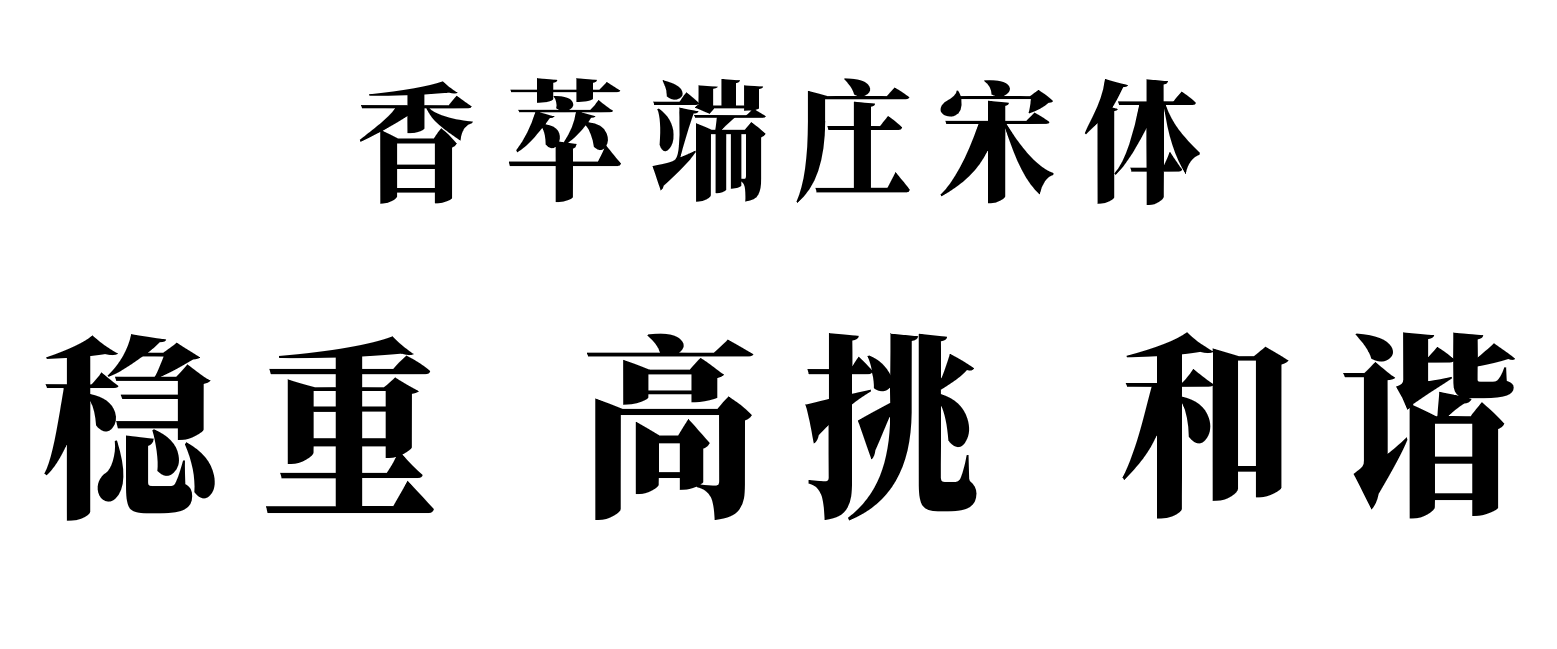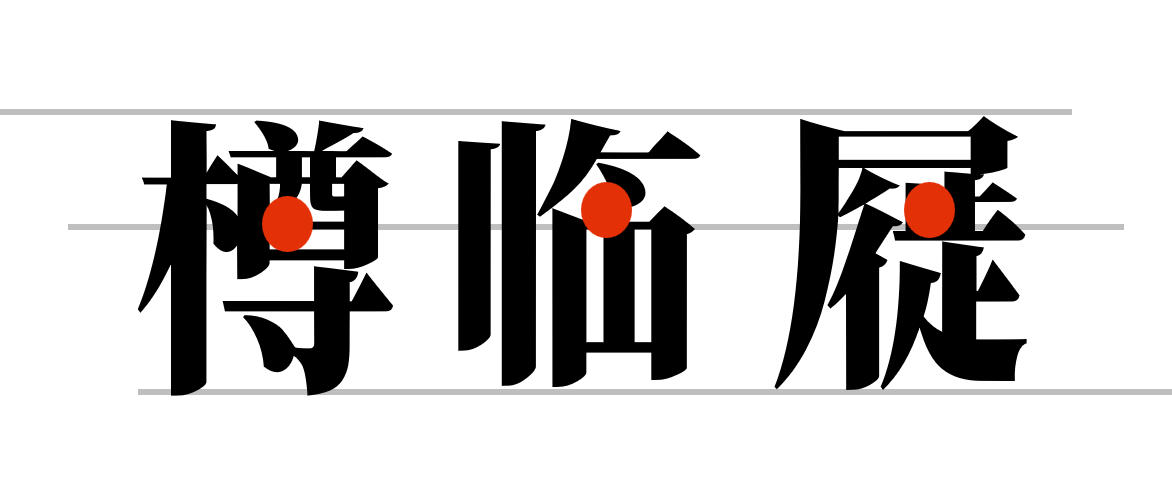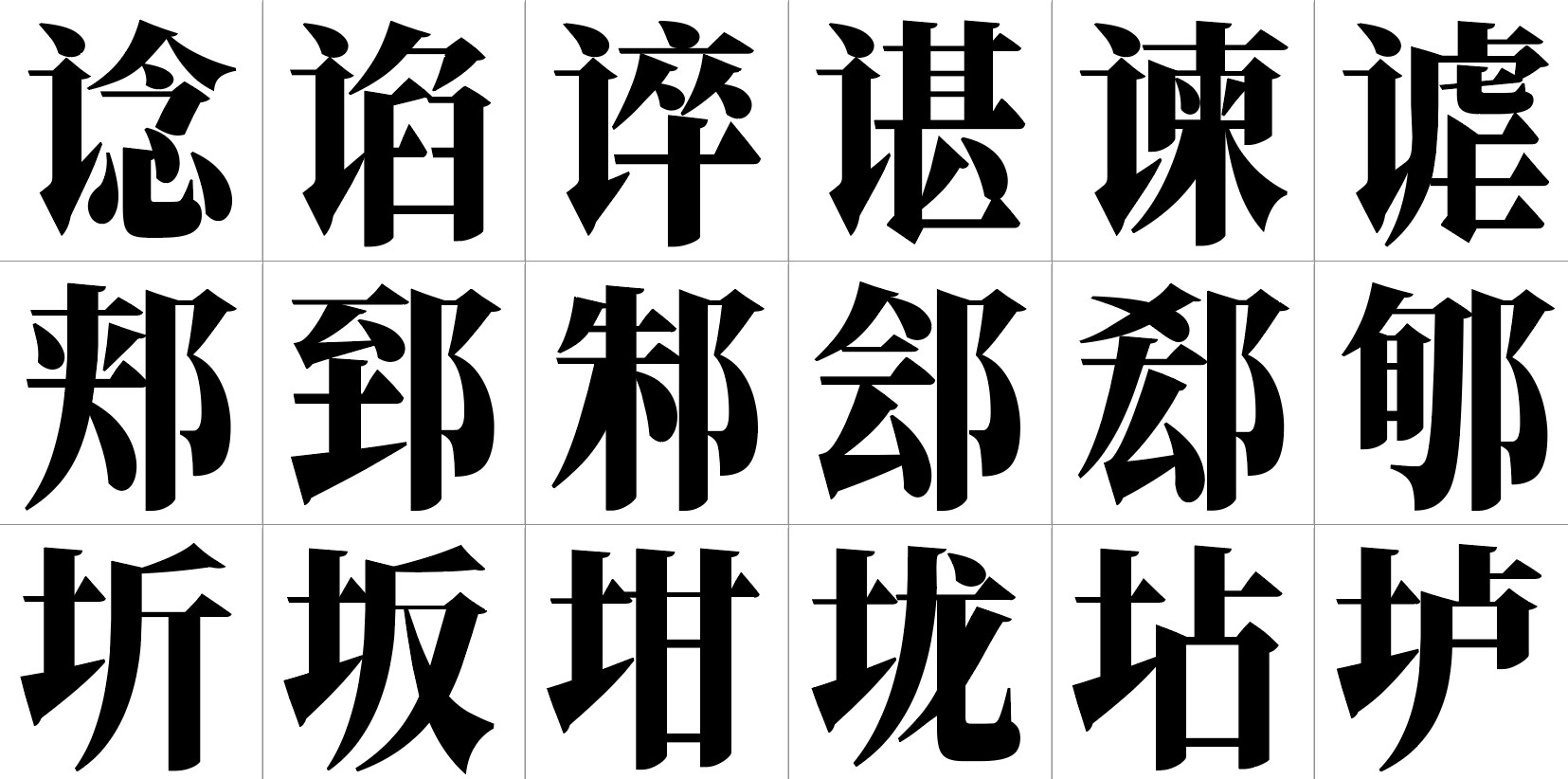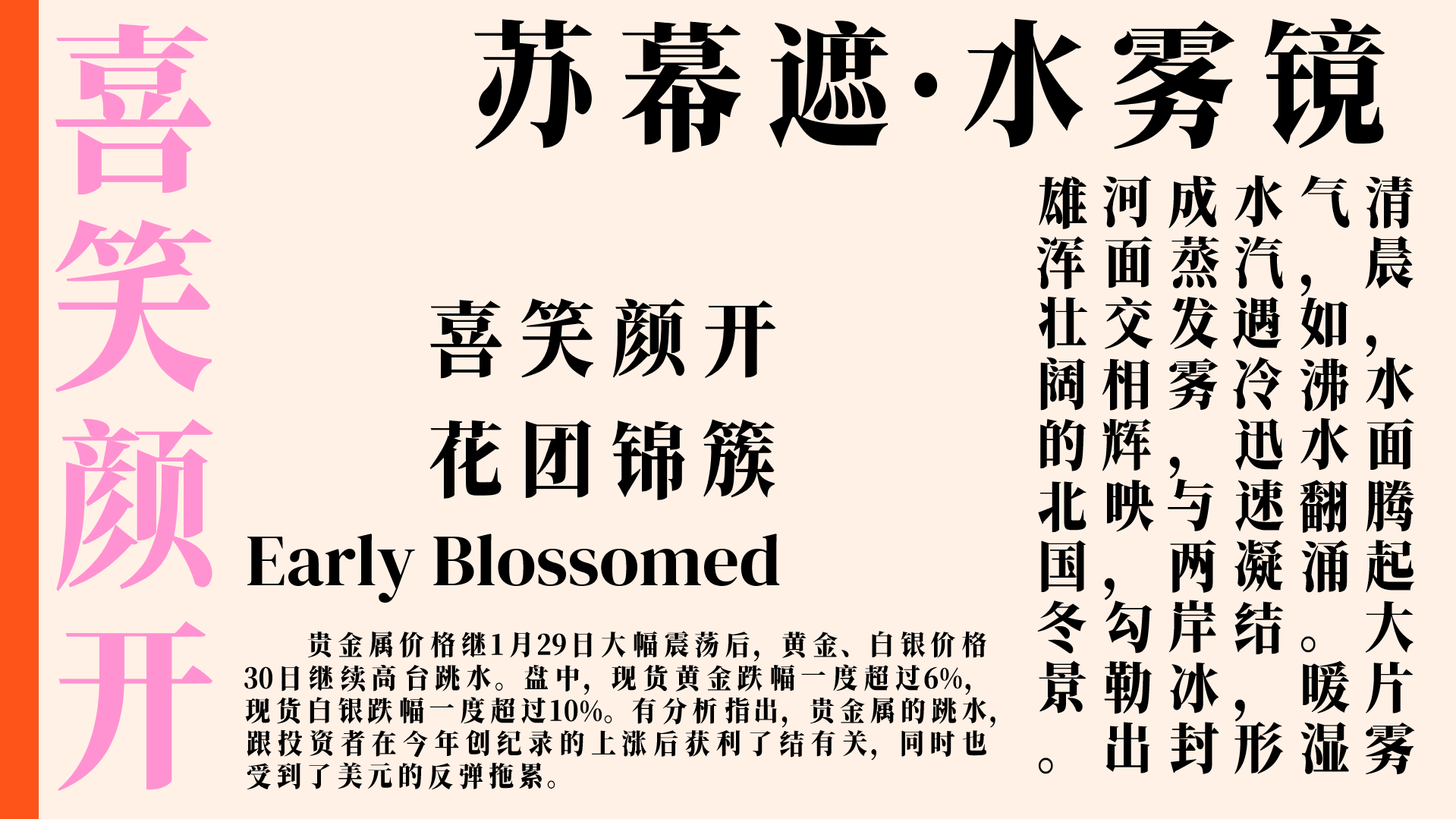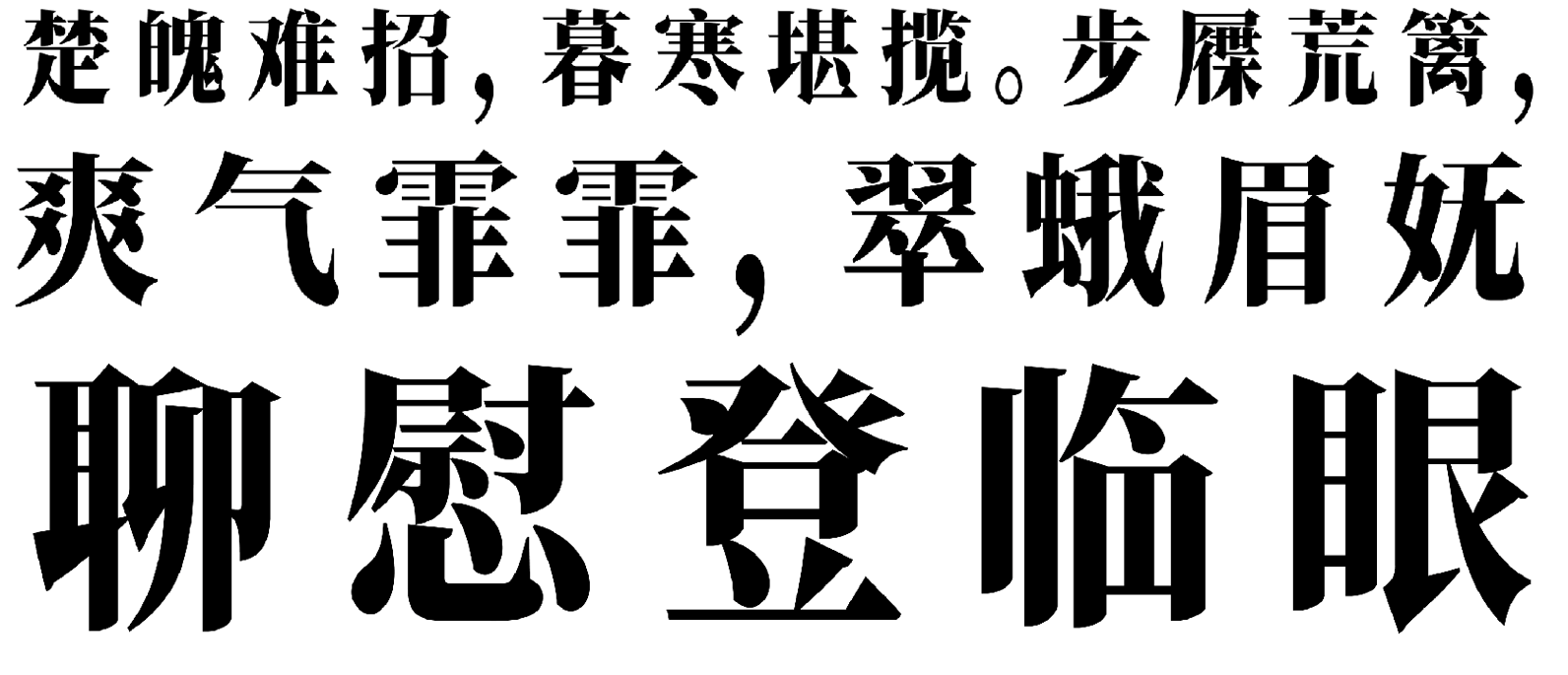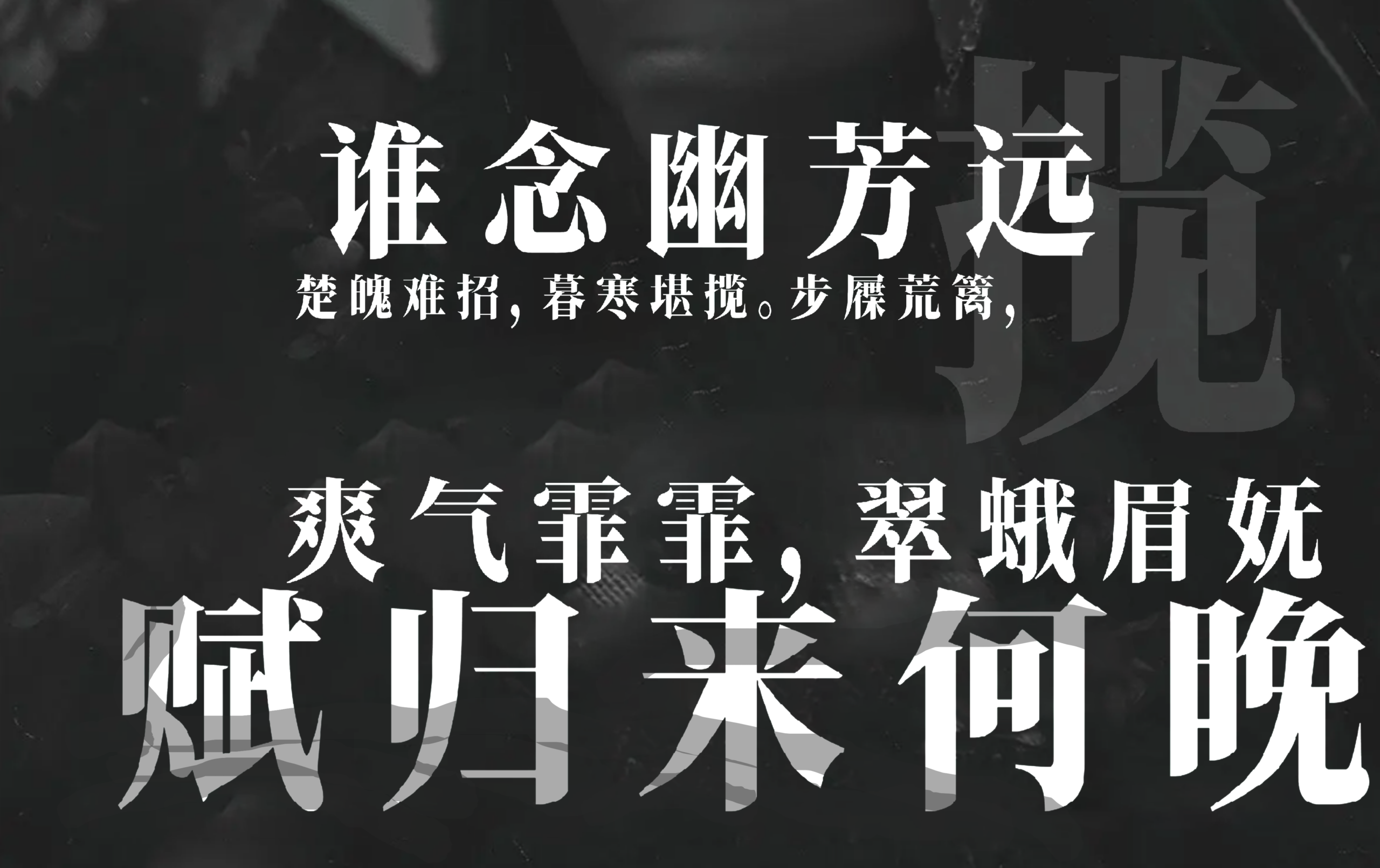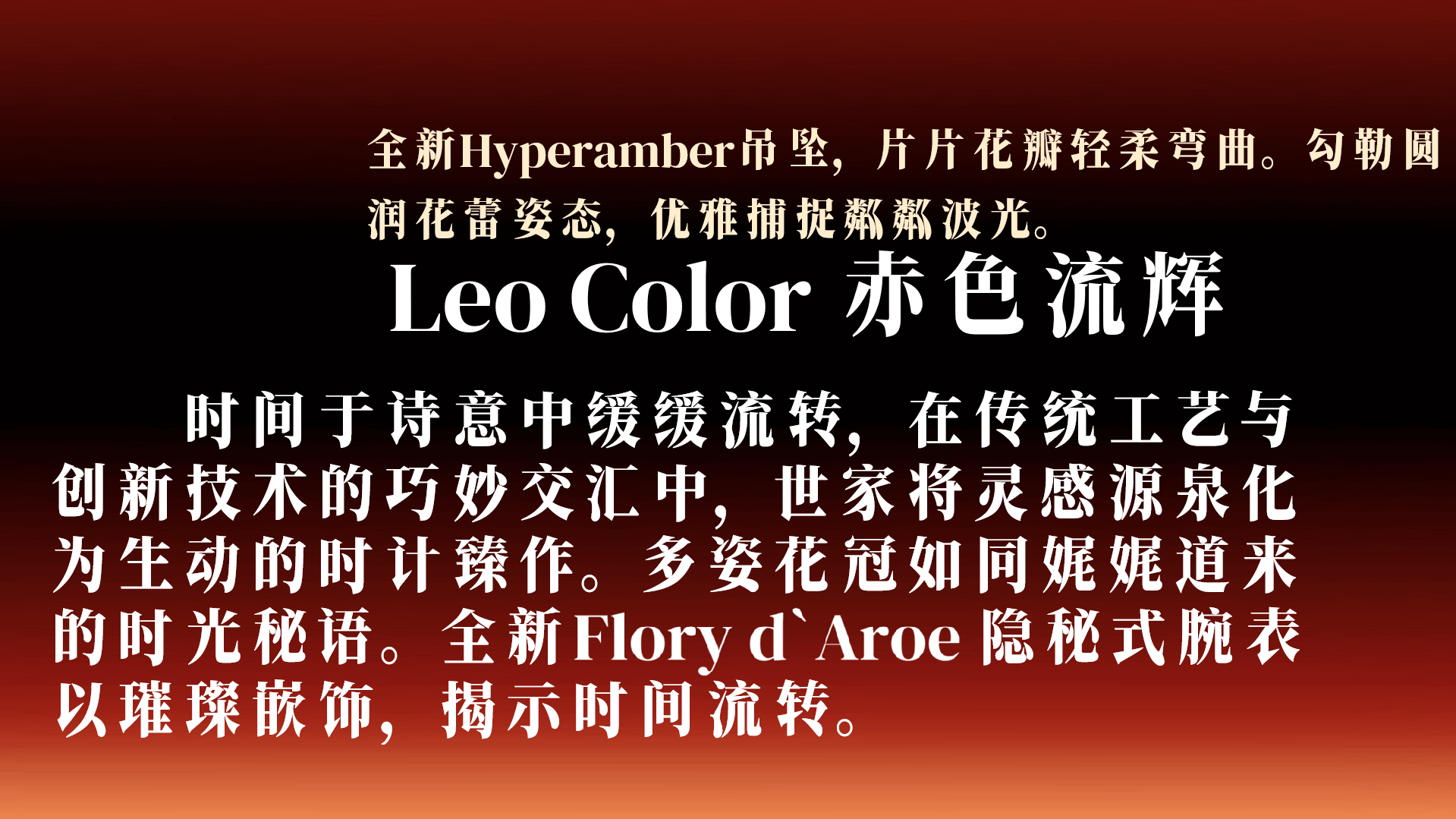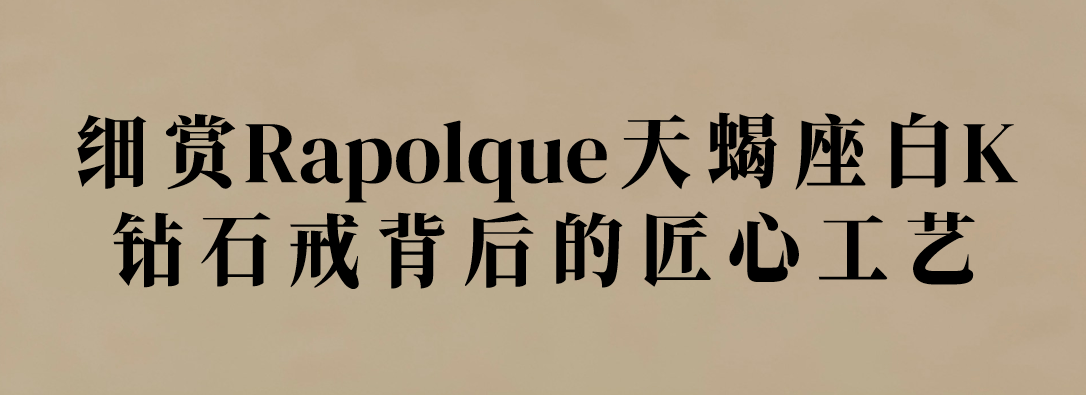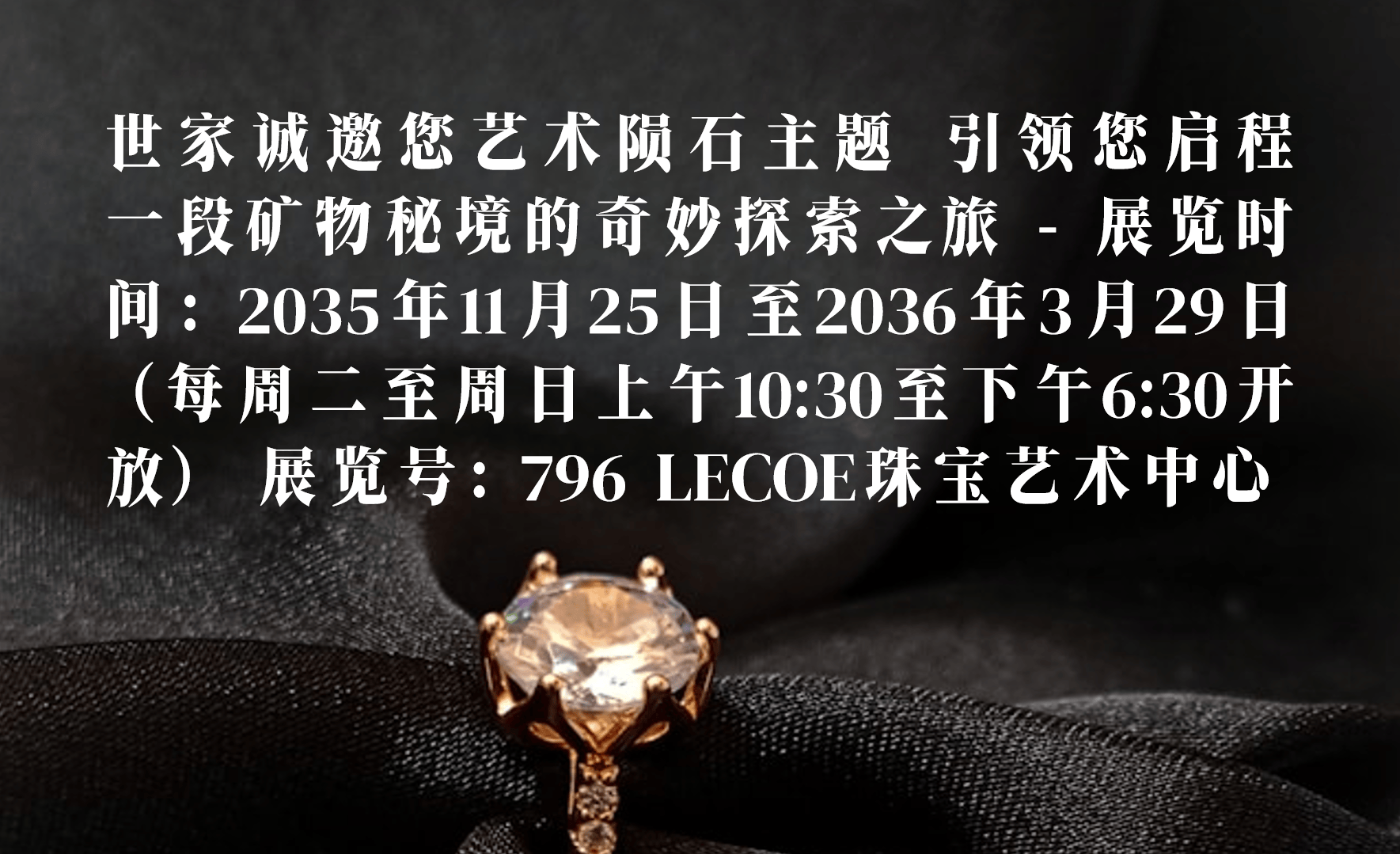
香萃端庄宋体字体示例,显示稳重、高挑、和谐特点
香萃端庄宋体是一款采用GB2312编码的开源免费字体。字形高挑,整体修长,笔画粗细中等。笔画清健饱满,整体感观协调,视觉速度平缓。
为了满足更加现代、时尚的标题和正文用字,刻意拉高了重心,产生强烈的对比。这些特征使它更为简洁现代。
三个汉字“樽临屇”,每个字的一个笔画上标有红点,用于展示字形结构。
笔画细节干净利落,重心大致分布在3/8处,呈现冷静、锐利、简洁的效果。
不同字号的排版
虽然重心拔高夸张,但正文和标题应用效果都很好,保持和谐的美感
三行六列的楷体书法汉字展示,包括“谂、谄、谇、谌、谏、谑”等字。
中文文本图片,标题为'苏幕遮·水雾镜',包含喜笑颜开等短语、一段冬景描述和贵金属价格新闻。
香萃